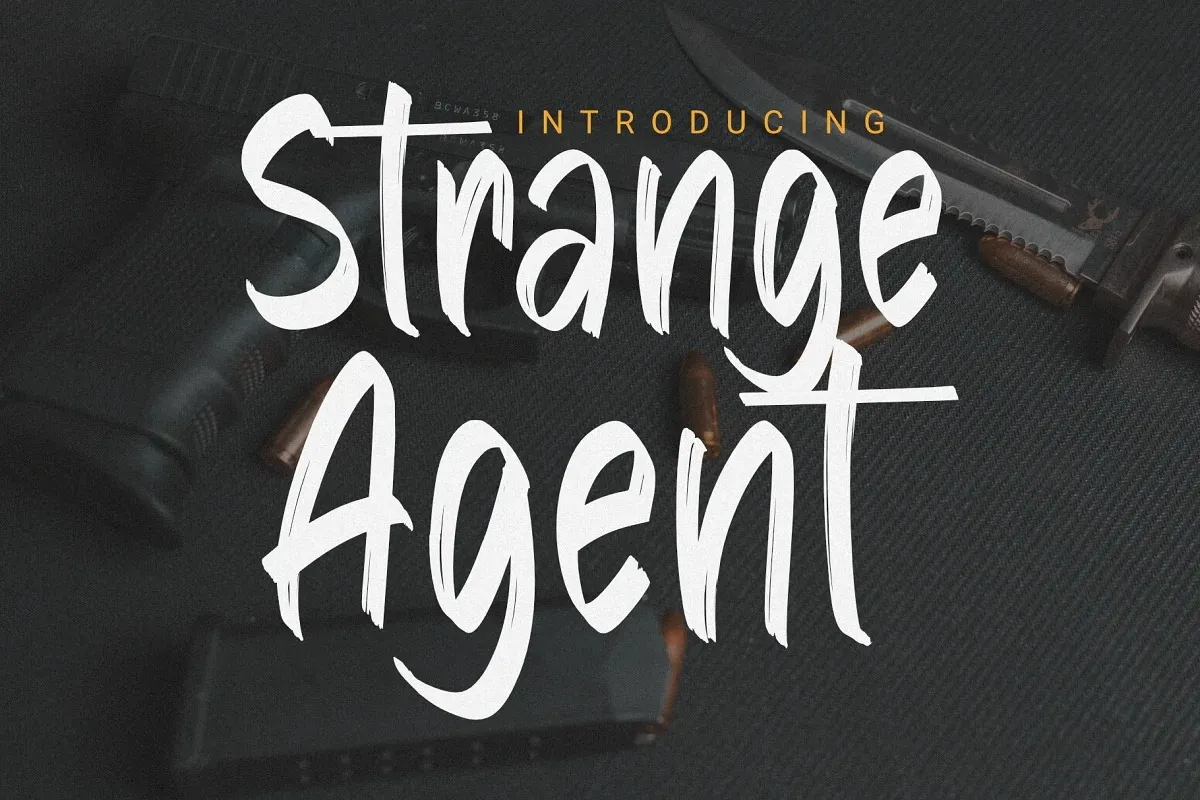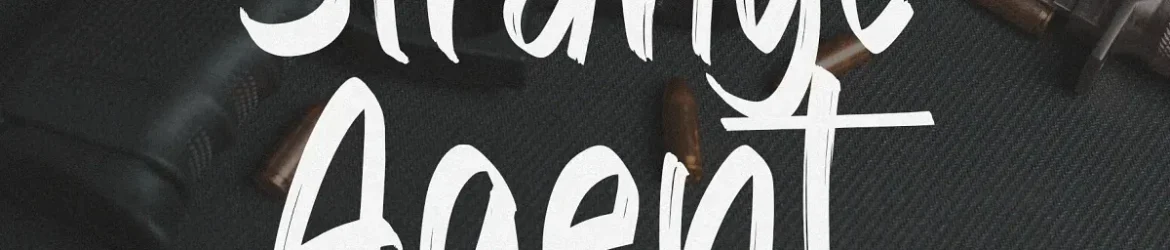
A Strange Agent é uma fonte script que oferece a sensação natural do desenho manual combinada com um moderno refinamento. Este estilo de escrever tem textura, dando-lhe uma aparência única e vibrante. Seu uso adequado pode transformar qualquer design em algo inovador e autêntico. Esta fonte é ideal para trabalhos que exigem um toque único e pessoal, como logotipos, designs de mídias sociais, criações de marca, conteúdos digitais, anúncios, embalagens de produtos, subtítulos, cartazes, materiais de merchandising e muito mais. A Strange Agent é uma escolha perfeita para quem deseja dar vida às suas ideias com um design elegante e autêntico.